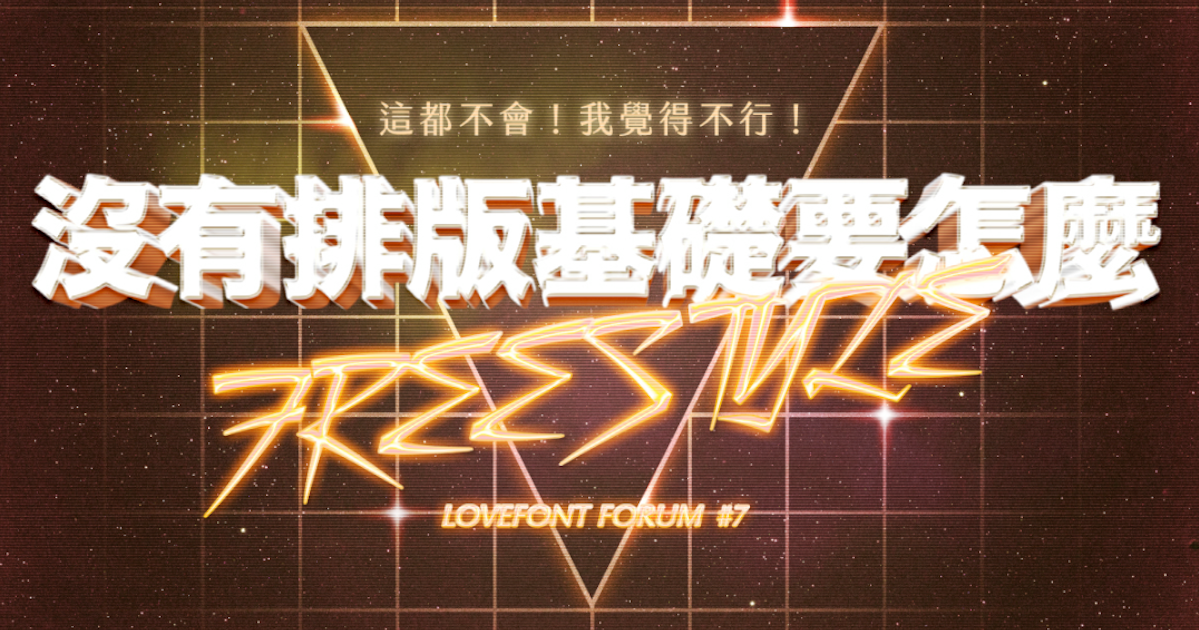
【字戀講座在華山 #7】沒有排版基礎要怎麼 Freestyle
字戀講座是
由 justfont 主辦、籌劃的全新免費字型講座,
除了希望能推廣字型相關知識外,
也希望讓大家更深入瞭解字型設計的文化、歷史、技術、哲學⋯⋯
每次講座前半場,都會帶給大家台灣民眾必修的基本的字型知識,
也會在後半場依照時事、互動調查需求來規劃有趣的次領域主題,
希望能用輕鬆好玩的方式,讓大家更親近這個與我們息息相關的領域。
講座介紹
「排版不就是選字型放字型嗎,就 freestyle 啊」
「⋯⋯我覺得不行。」
「排版是一門專業,沒有基礎要怎麼 freestyle?」
「安安你字型系?」
第 7 場:沒有排版基礎要怎麼 Freestyle
(連這都不會?我覺得不行!)
排版就是選字放字配圖片?
別給我騙,編排是個專業。
大中小書看一遍,
也不見得就會。
要養成的是基本觀念。
師父引進門修行在個人,
比例主從群化不能不細分。
這就是我的 Freestyle(?)
關於講者與主題
Julia,資深編輯人,專職版面圖文整合、編輯架構。英國諾桑比亞大學設計學院博士肄業,研究主題為橫直混排版面的閱讀順序,於設計、出版媒體工作多年。本次講座,會主要集中於編排的核心觀念:字體在版面上的面積分配,以及大小不同的字號所需肩負的任務等等。一言以敝之,即「基本的基本」,大概細分爲三方面:
一、比例,大小怎麼分
二、順序,先後主從誰是大王
三、群化,你家不是我家